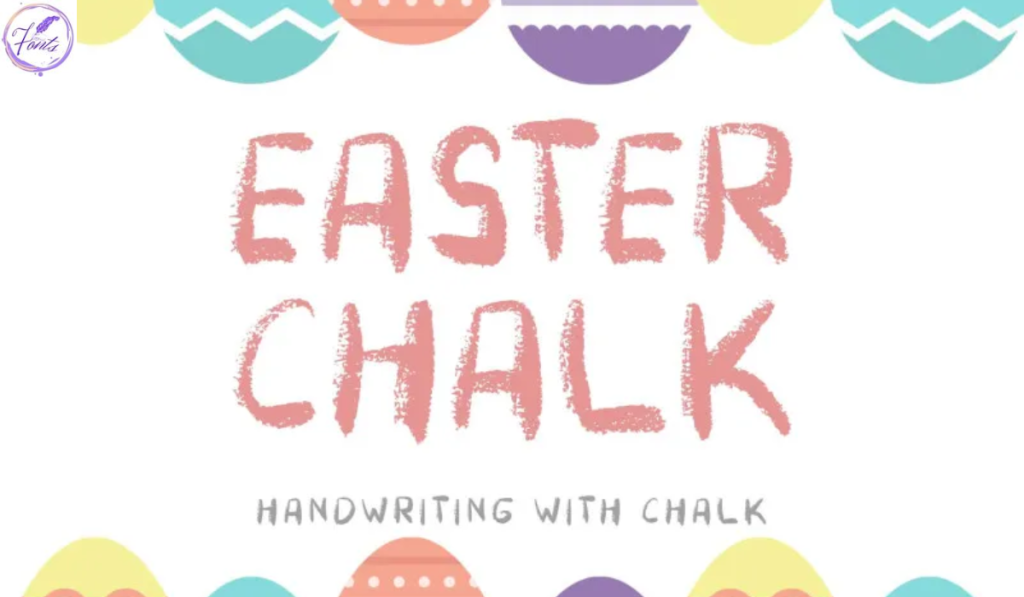
Font TP Easter Chalk Việt hóa
Tác giả: Yoga Letter
Ngôn ngữ: Tiếng Việt và một số ngôn ngữ khác
Bộ Font: TP Easter Chalk
Phân loại: Phấn, cá tính
Kiểu chữ: Không chân
Nếu bạn đang tìm kiếm một phông chữ mang hơi thở của ngày lễ Phục sinh, đầy vui tươi và sáng tạo cho các dự án thiết kế của mình, font tp easter chalk chính là lựa chọn tuyệt vời. Được thiết kế bởi nghệ sĩ tài năng Yoga Letter vào năm 2022, tp easter chalk font lấy cảm hứng từ những nét vẽ phấn sống động trên bảng đen. Với những đường nét ngộ nghĩnh, đáng yêu và các họa tiết trứng Phục sinh tinh nghịch, font tp easter chalk mang đến một không khí tràn đầy niềm vui và sự phấn khởi cho mọi thiết kế. Phông chữ này đặc biệt phù hợp cho các dự án liên quan đến trẻ em, giáo dục, và các sự kiện đặc biệt như sinh nhật, lễ hội. Phiên bản Việt hóa của font tp easter chalk được thực hiện bởi nhóm Fonter.vn, giúp các nhà thiết kế Việt Nam dễ dàng sử dụng phông chữ này trong các sản phẩm của mình.
Đánh giá font tp easter chalk
Font tp easter chalk đã nhanh chóng chiếm được cảm tình của đông đảo người dùng kể từ khi ra mắt vào mùa Phục sinh năm 2022. Theo thống kê từ Dafont, tp easter chalk font đã được tải xuống hơn 100.000 lần chỉ trong vòng 1 tháng, trở thành phông chữ miễn phí được yêu thích nhất trong thể loại phông chữ Phục sinh. Nhiều trung tâm giáo dục và thương hiệu đồ chơi nổi tiếng như ILA, Việt Tinh Anh, và LEGO cũng đã lựa chọn font tp easter chalk cho các chiến dịch quảng cáo và sự kiện của họ.
Năm 2023, tp easter chalk đã giành giải Vàng tại Cuộc thi Sáng tạo Phông chữ Việt Nam (VFDC) ở hạng mục Phông chữ Sự kiện. Với sự kết hợp hoàn hảo giữa tính thẩm mỹ và tính ứng dụng, font tp easter chalk xứng đáng là một công cụ đắc lực cho mọi nhà thiết kế muốn mang đến một hơi thở vui tươi, trẻ trung cho các sản phẩm của mình.